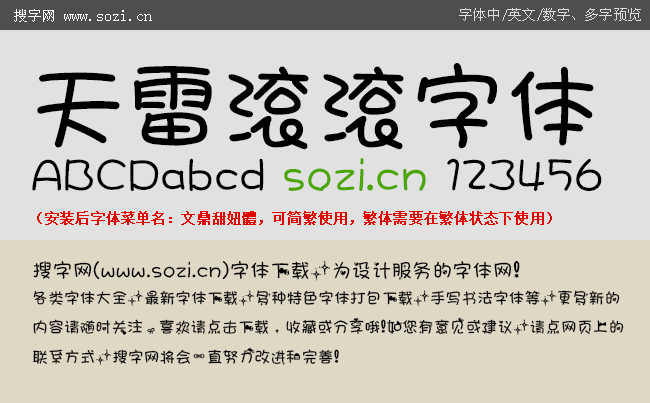
天雷滾滾字體
搜字網給大家提供一款很卡通的手機中文字體下載。修改者給這款字體叫天雷滾滾字體,這款手機中文字體以文鼎甜妞體為原形,將個別筆畫替換為卡通圖案,文鼎甜妞體的筆型渾厚圓潤,字構活潑可愛,不同于一般傳統字型的刻版印象。具有青春活力、甜美可愛、自由、創新的特色。充滿孩童般童趣的天真氣息,在筆畫間嵌入卡通圖形,增加了趣味性,非常適合喜歡卡通的朋友在手機上安裝使用。